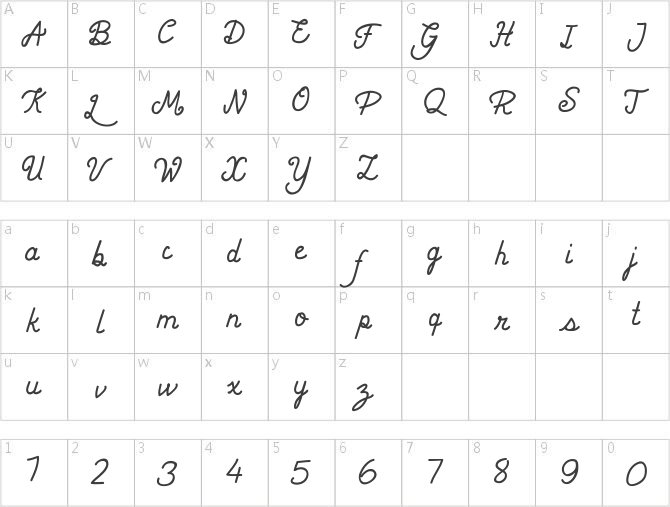
CFChevalierdeLorimier-Regul
CFChevalierdeLorimier-Regul介绍
CFChevalierdeLorimier-Regul字体字库是一款让人赏心悦目、百看不厌的英文字体,适合各类广告和产品包装设计应用,字体大小0.1MB,格式为ttf字体,上传用户是晓语无声,作者/版权方为未知
CFChevalierdeLorimier-Regul效果图